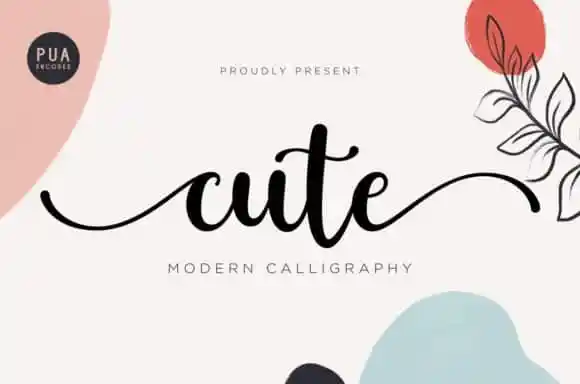
Cute Calligraphy Font – Fonte Grátis
Cute Calligraphy Font
A fonte ‘Cute Calligraphy Font’ é uma escolha perfeita para designers que buscam um toque delicado e moderno em seus projetos. Desenvolvida pela 99designs, ela combina a elegância do script com o charme dos traços de letra escrita a mão, criando um efeito irresistivelmente romântico. Perfeita para criar cartões de agradecimento, convites casamento, selos pessoais ou design gráfico em geral, este script é perfeitamente adaptado para dar vida às suas criações. Suas características delicadas e arredondadas trazem uma sensação casual e despojada que se torna irresistivelmente sábia e alegre. Esta fonte é ideal para incorporar elementos pessoais em designs digitais, ou seja, ela não apenas dá um tom jovial às suas criações, mas também permite que você adicione um toque delicado e único. Sem dúvidas, esta é uma opção de fonte imprescindível para qualquer designer em busca de uma fonte com o toque romântico e elegante da aquarela moderna.